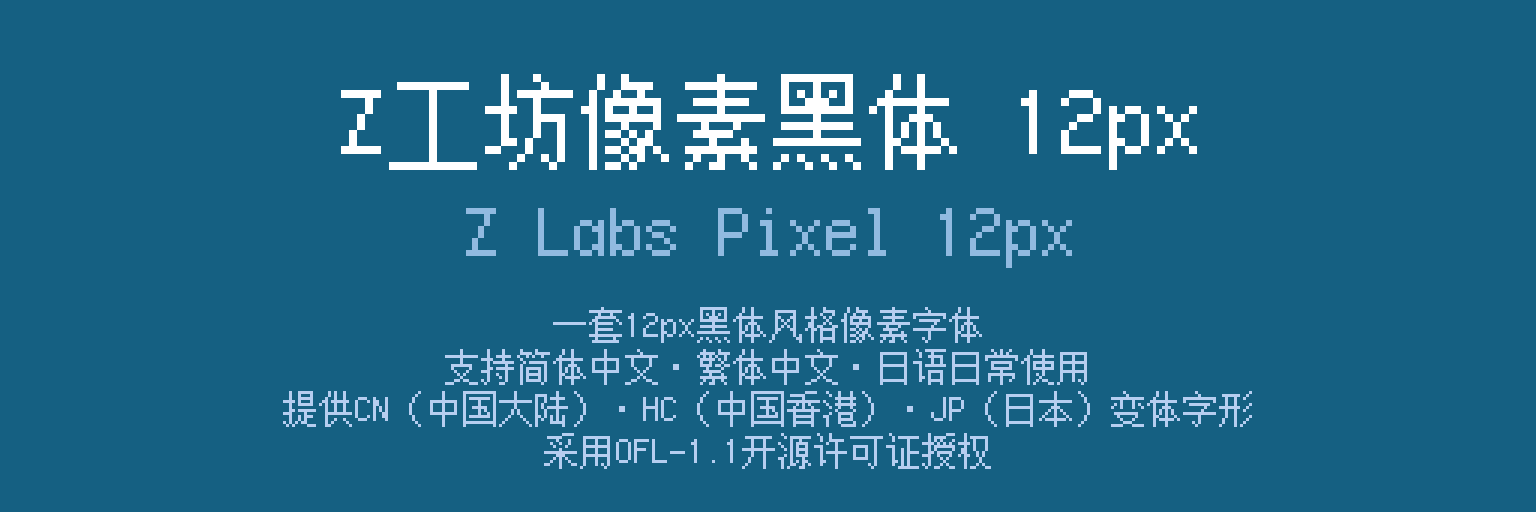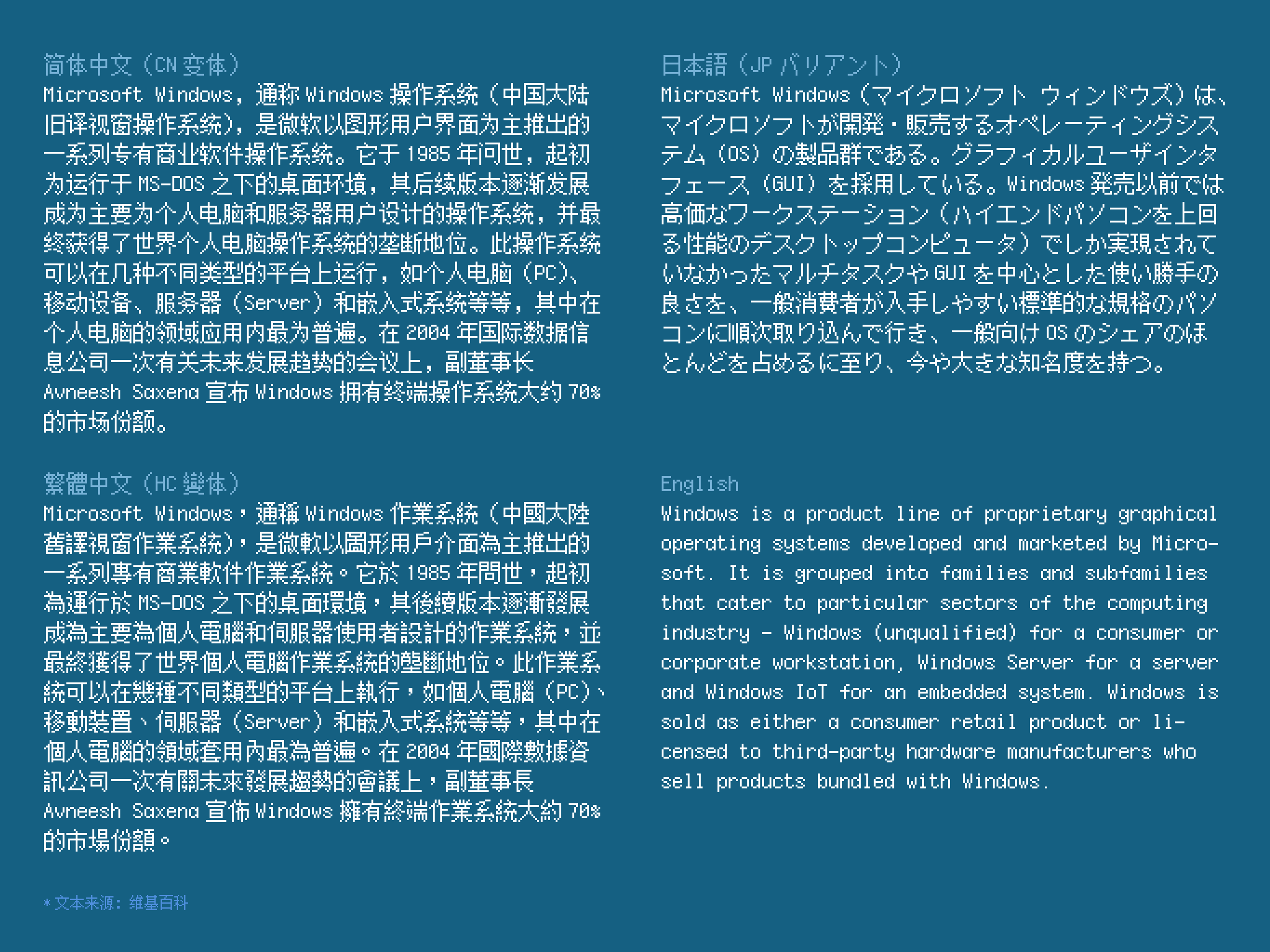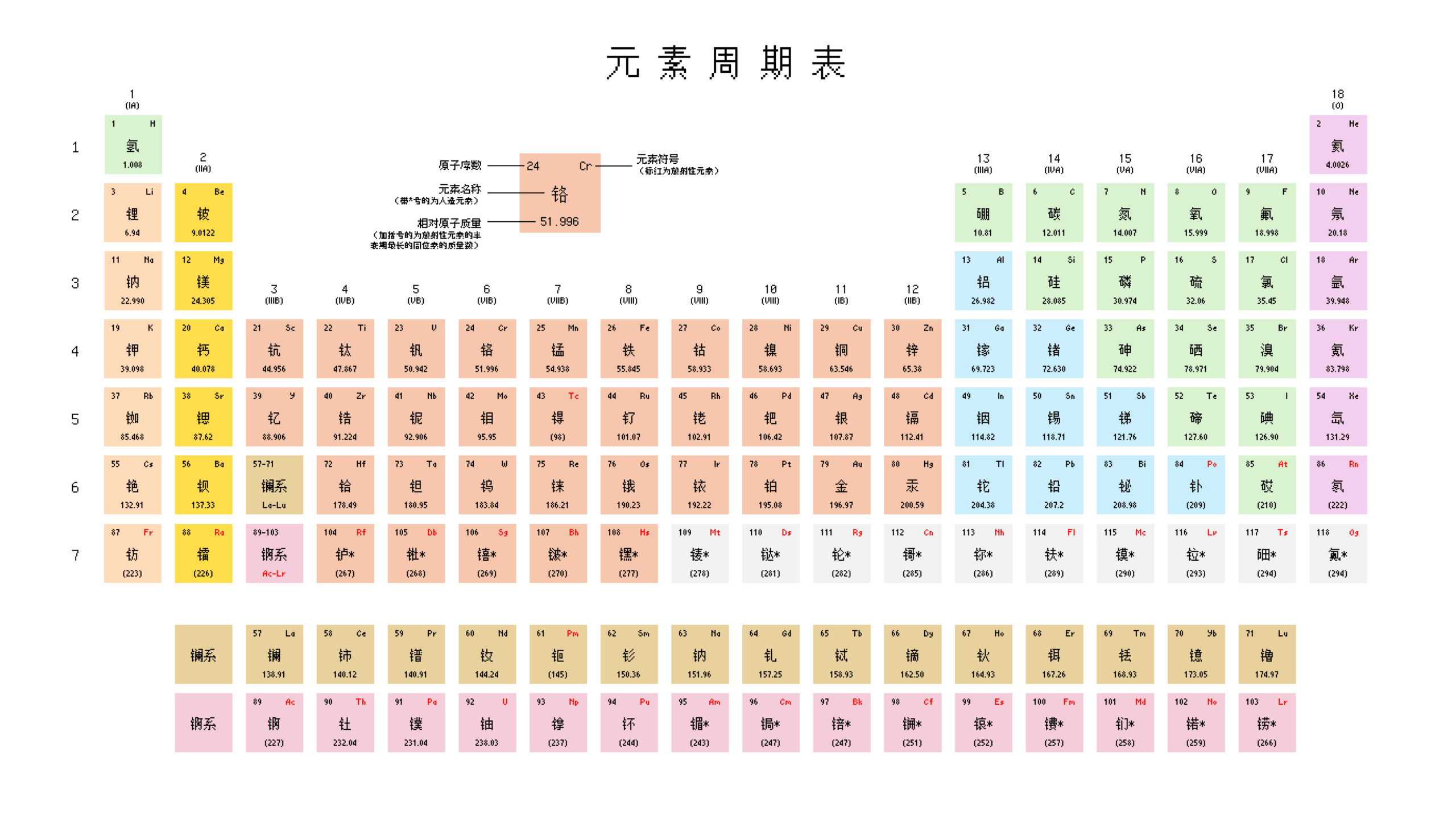
「Z工坊像素黑体 12px / Z Labs Pixel 12px」
「Z工坊像素黑体 12px」(Z Labs Pixel 12px) 是一款规格为 11*12px 的像素字体,采用黑体字形风格,具有中国大陆、中国香港、日本三种变体字形,西文字体按等宽规格设计。
字体目前已基本支持简体中文、繁体中文、日语的日常使用。
字体示例
字形变体
本字体具有CN(遵循中国大陆标准)、HC(遵循中国香港标准)、JP(遵循 JIS X 0213:2004 标准)三种变体,可满足不同环境下的使用需求。
由于不同地区的用字习惯不同,选择一个恰当的字形变体十分重要。我们建议您在简体中文环境下选择 CN 变体,在繁体中文环境下选择 HC 变体,在日语环境下选择 JP 变体。
对于繁体中文用户,若您无法接受中国香港字形标准,建议您使用其他字体。
字体覆盖范围
汉字
本字体不同版本变体的汉字支持情况不同。下面列出了每个版本变体的制作计划与具体支持情况。
中国大陆变体字形(CN)
ℹ️ 共计支持汉字:12994
中国香港变体字形(HC)
ℹ️ 共计支持汉字:10082
日本变体字形(JP)
ℹ️ 共计支持汉字:6365
⚠️ 鉴于日语对汉字需求较小,若无特殊情况,日标字形将不再制作新的汉字字符。
由于作者精力有限,目前 HC 版与 JP 版仅制作了部分汉字,因此在使用中可能会遇到缺失汉字的情况。
若软件支持多字体排版,可以通过设置 font_family 或类似属性,使支持汉字数更多的 CN 变体作为 HC/JP 的后备字体,从而让 CN 变体显示 HC/JP 暂未支持的汉字。
若软件不支持多字体,可以考虑使用对应变体的 Fallback (FB)版本。在这个版本中,对于 HC/JP 变体已支持的汉字,将维持原样;对于 CN 变体已经制作而 HC/JP 未制作的汉字,将使用 CN 字形填充对应的码位(无论这个字是否在 HC/JP 制作计划中),使得支持汉字的数目与 CN 版一致(不保证字形正确性)。
注:三种字形变体的西文与符号部分保持一致(部分中文标点除外)。
| 平假名和片假名 | 支持(含半角片假名) | – |
| 拉丁字母 | 支持半角与全角两种格式的英文字母。同时也制作了大写字母的其他形式(🅰🅱等)。 | 未来会增加对其他拉丁字母的支持。 |
| 其他西文字母 | 支持西里尔字母与希腊字母(按半角规格制作)。 | – |
| 数字 | 包含半角数字和全角数字及 3 种格式的数字序号。 | – |
| Emoji 符号 | 支持以下字符:♿⛔✅❎㊗️㊙️🆎🆑🆕🆖🆗🆘🆚🈚️🈯️🈲️🈴️🈵️🈶️🈷️️🈸️🈹️🈺️🉐️🉑️🏧💹🔟🔠🔡🔢🚫🚾 (仅支持纯色样式)。 | – |
| 标点及其他符号 | 目前支持部分的标点及其他字符。 | 未来会增加更多字符。 |